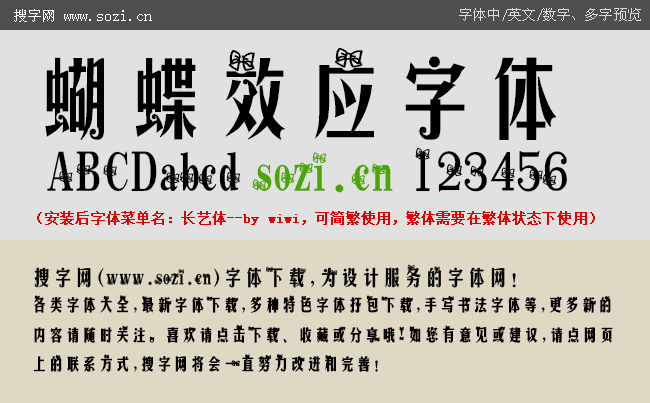
蝴蝶效应字体
搜字网给大家提供一款蝴蝶效应字体手机中文字体下载。这款手机字体是在汉仪长艺体笔画间插入了卡通蝴蝶图案。长艺体既有黑体的粗壮醒目,又有宋体的秀美柔和,加上艺术性的圆球形点、起笔如蝌蚪形的顿点、螺蛳转似的小钩,配以修长的字形,如少女般婷婷玉立,袅娜动人,美观而不落俗套。加入了卡通图案后又增添了艺术性,特别适合喜欢手机字体个性一些的朋友在手机上安装使用。